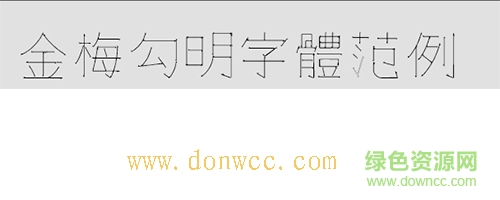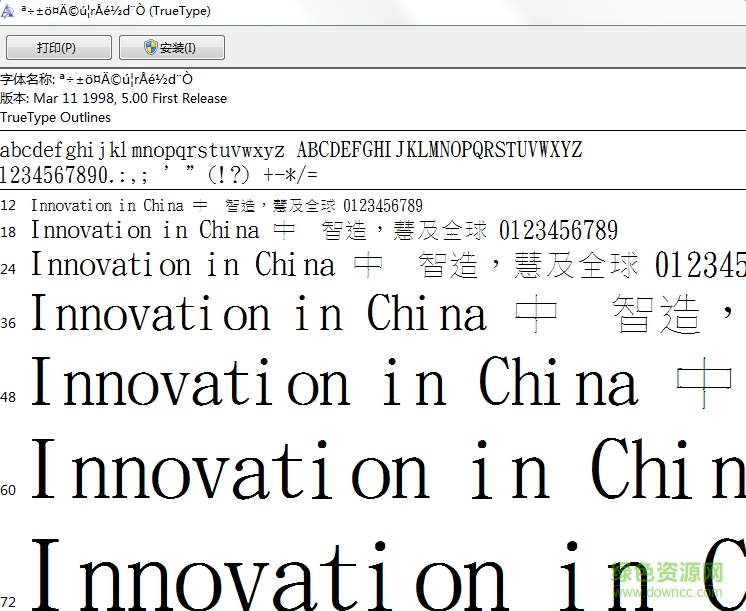
金梅勾明字體是一款金梅字體官方打造的勾明字體,官方打造而成,適合美工藝術(shù)設(shè)計(jì)等用戶需求,讓你的字體充滿明朗的線條性,喜歡就來綠色資源網(wǎng)下載吧!
金梅勾明字體用于美工設(shè)計(jì)方面的字體,該字體線條較細(xì)但結(jié)體勁練,用筆斬截,看上去十分美觀,整體效果非常統(tǒng)一,且字庫完整,可以廣泛應(yīng)用于廣告設(shè)計(jì)、出版印刷、包裝打印、ppt、影視制作以及內(nèi)容用字等領(lǐng)域,有需要的朋友可以免費(fèi)下載收藏。